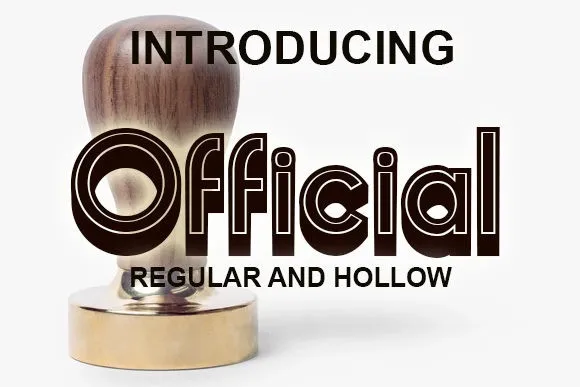
A ‘Official Font Family’ é uma linhagem de tipo sans serif que Vladimir Nikolic desenvolveu com um estilo moderno e elegante. Perfeita para ambientes digitais, essa família de fontes oferece três estilos únicos que se destacam em diversas categorias. Ela traz o conforto e a simplicidade do tipo livre de serif para um uso casual, mas também adota um ar de sofisticação quando é usada nas áreas como Beleza, Tecnologia, Jogos, Revistas, Música e Esportes. Seja você designer ou criador de conteúdo, essa família de fontes é o refletor do seu estilo em qualquer projeto visual. Com uma estética que combina modernidade com uma certa elegância, a ‘Official Font Family’ não apenas oferece uma alternativa agradável ao tipo tradicional, mas também traz uma nova dimensão à sua paleta de ferramentas digitais.